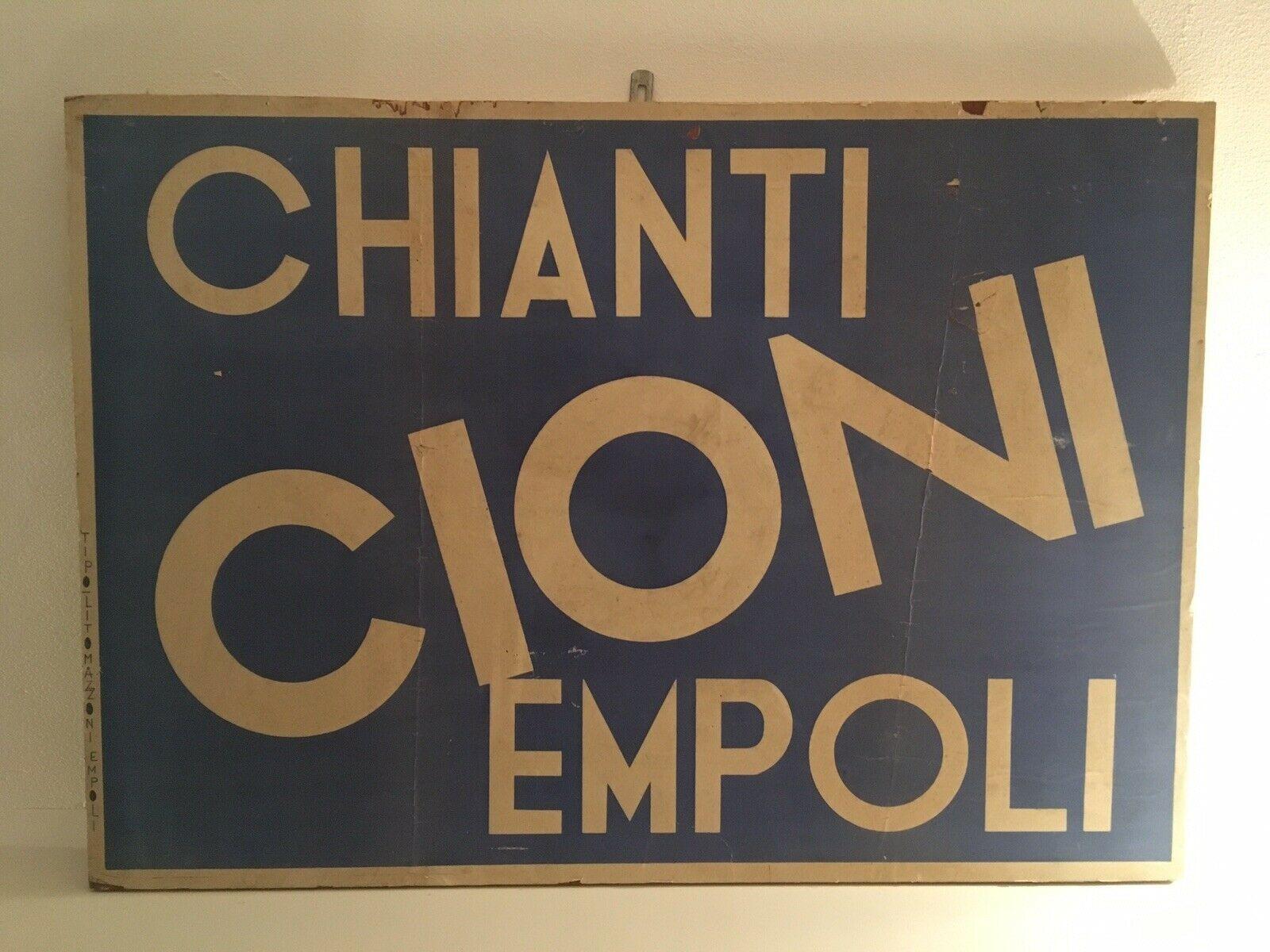
Suche Schriftart aus Chiantiwerbung 1950er-Jahre (allenfalls früher)
Bin kein Schriftprofi, aber interessiert an Gestaltung, und suche deshalb die Schrift auf der Chianti-Werbetafel, die im Anhang zu sehen ist. Es darf auch eine (sehr) ähnliche sein und sie darf natürlich etwas kosten, wenn sie gut ist.
Schriften dieser Art entstanden im Italien der 1920er und 1930er. Man fand diese auch auf den Werbeplakaten der italienischen Faschisten. Leider habe ich gerade keine Links auf Beispiele parat. Die Stichworte für die Suche wären: 1930 geometric italy
Viel Spaß beim durchwühlen. Was mir bei der Werbung aufgefallen ist: Das M ist spitz, das N stumpf. Bei den meisten Schriften waren grundsätzlich M und N entweder spitz oder stumpf in der Benutzung. Im Schriftsatz waren da immer beide Versionen. Das wäre heute in den Opentype-Features.
An die dachte ich zwar auch, aber die war mir viel zu weit weg von der Reklame. Aber wenn Du die Semplicità schon erwähnst, gebe ich mal ein paar Informationen zu einer freien Version an.
Typeface:    Semplicità
Designer:    Alessandro Butti
Year:        1930
Publisher:    Nebiolo foundry
Wird in Italien als Schrift der Faschisten gesehen.
Ähnlicher wären da vielleicht:
Lemon Milk: https://www.dafont.com/lemon-milk.font
Libby: https://www.dafont.com/libby.font
Novecento Sans: https://www.fontspring.com/fonts/synthview/novecento-sans
Wie stark ist  die Konnotation zum Faschismus denn? Würde bspw. ein Linker sofort sagen: "Aha, versteckter Faschist!" Oder ein Bildungsbürger generell? Ist nicht die Konnotation, die ich da dann drin haben möchte.
Ganz andere, weiterführende Frage: Kann es sein, dass die Werbung auf einem von Hand gezeichneten Klischee/Schrift beruht und es diese so allenfalls tatsächlich in der Art gar nicht gibt? Ein Hinweis für mich wäre die Signatur links, zudem die Anmerkung weiter oben :
Das M ist spitz, das N stumpf.
Wird in Italien als Schrift der Faschisten gesehen.
„wird gesehen als …“ bedeutet aber doch, dass es eine Konnotation gibt, oder?!
Dann ist es langsam Zeit, sich die Schrift zurück zu holen!
Gibt es denn überhaupt einen Beleg für die Aussage?
hab auf die schnelle lediglich das hier gefunden:
Einfach mal folgendes ansehen und dann sollte man ein Gefühl für diese Schriften bekommen:
Mostra Nuova
Inspired by Italian Art Deco poster lettering of the 1930s.
Designer: Mark Simonson
Year: 2009
Publisher: Mark Simonson